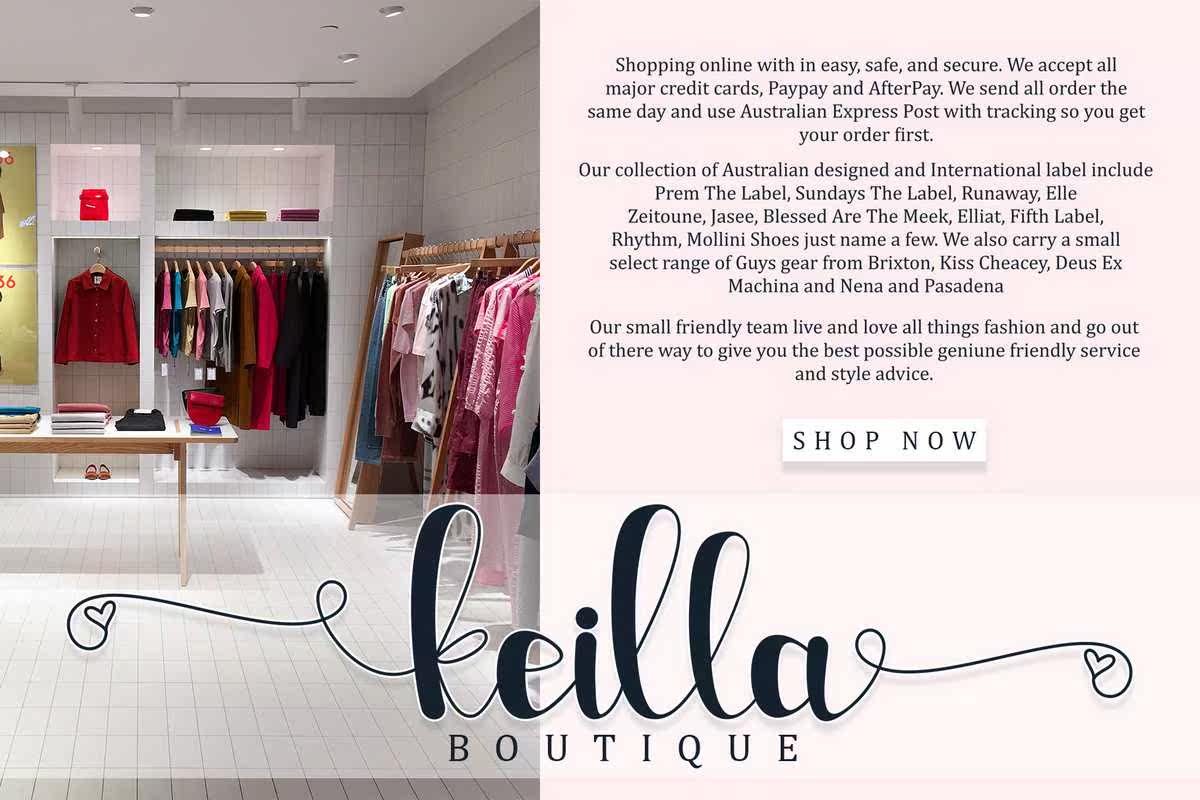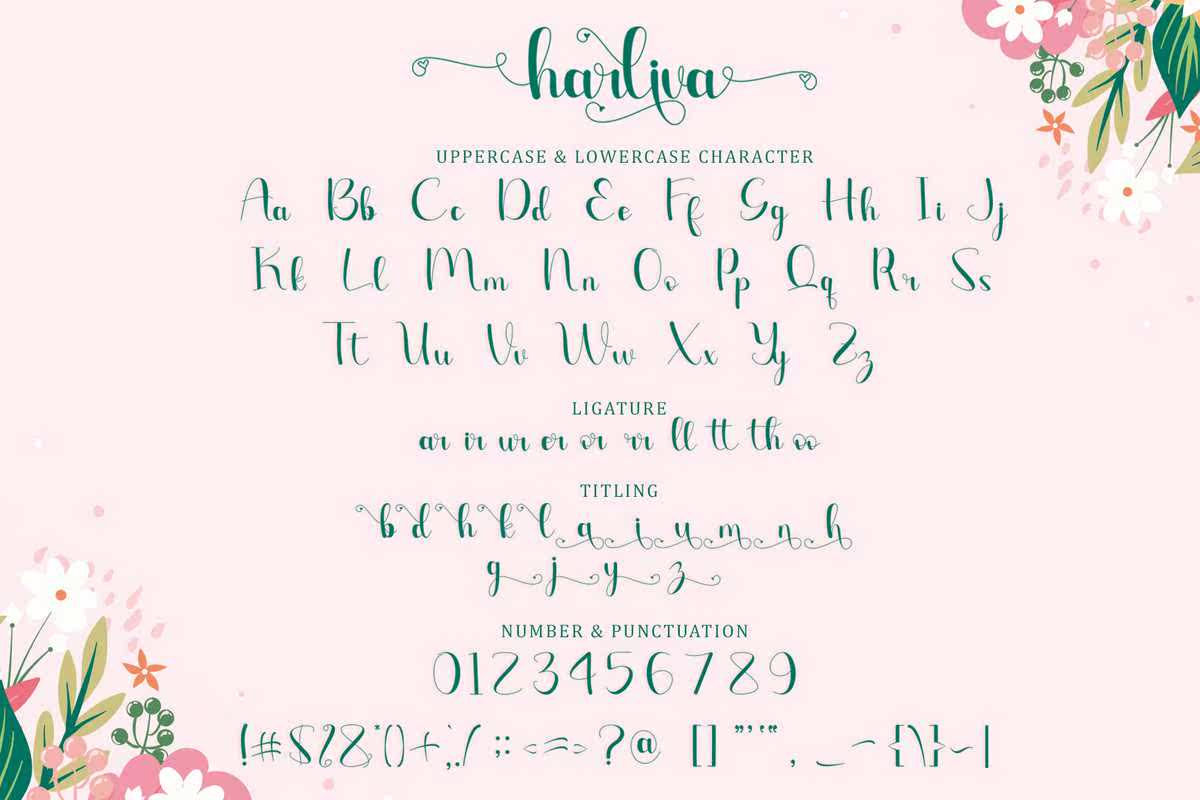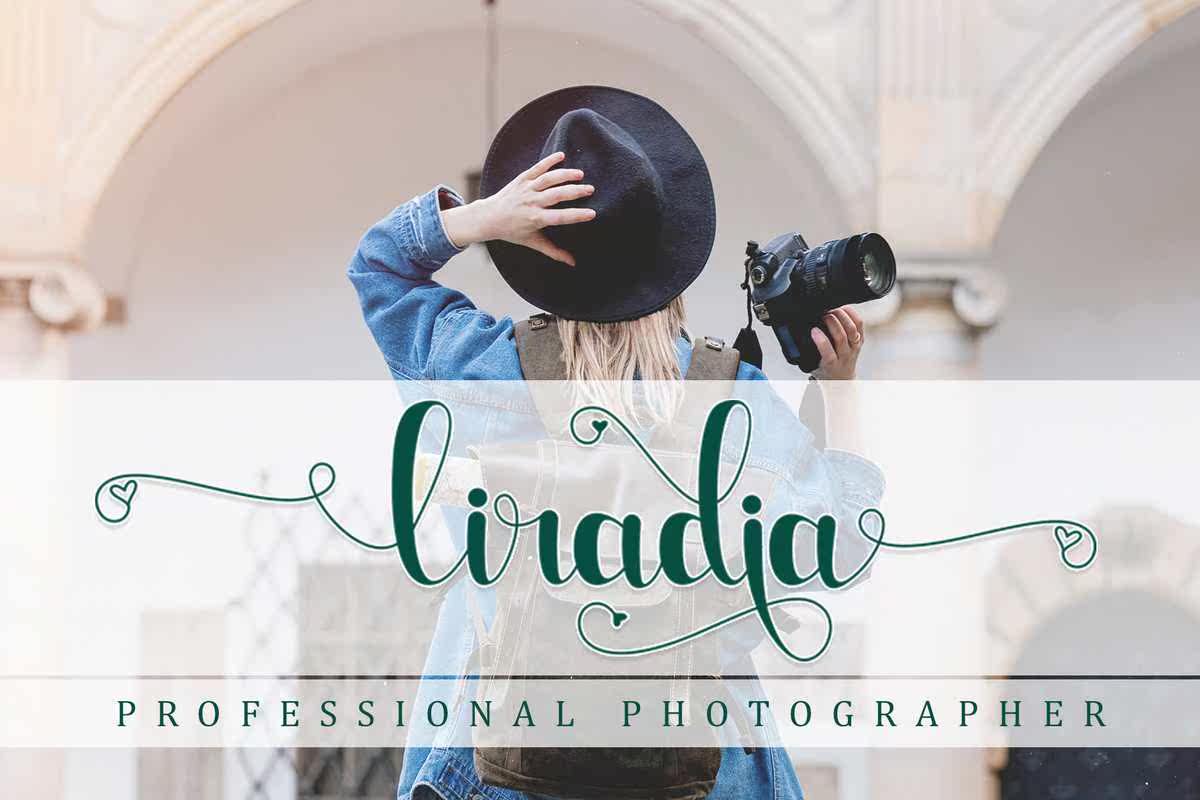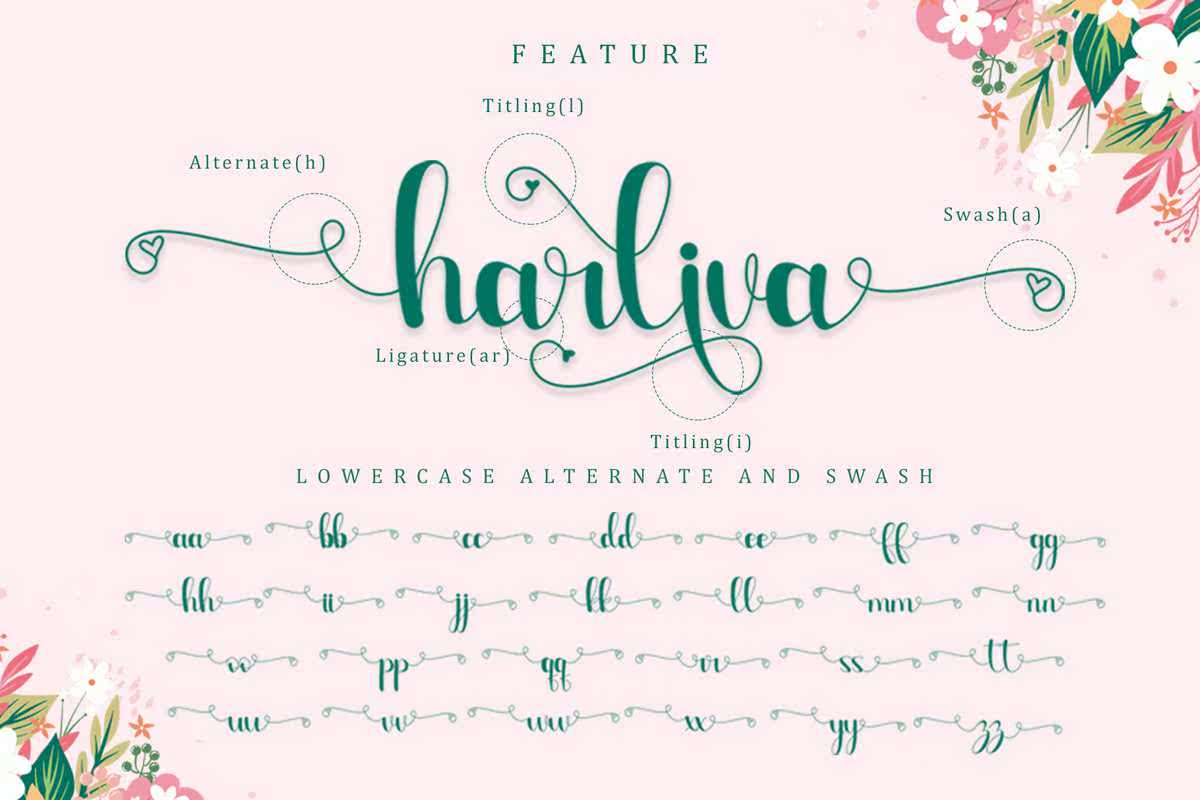
Harliva是一款现代书写字体。这款字体可以让您的书写和品牌更加优雅美丽。Harliva非常适合于独特的品牌、照片覆盖、水印、贺卡、海报、名片、邀请函、婚礼、摄影、时尚、服饰、信件、文具等。a-z,备选字体(a-z)和连字包括在你可以使用你的logo或ameacustom中,手写字体Hylokharliva是现代的书写字体。这种字体可以使你的书写和品牌优雅或美观。Harliv擅长于独特的品牌、照片覆盖、水印、贺卡、海报、名片、请柬、婚礼、摄影、时尚、服装、信件、文具、,等。包括一系列的洗涤液(a-z)、替代品(a-z)和结扎物,以便您可以使用您的标识或手写体、手写体